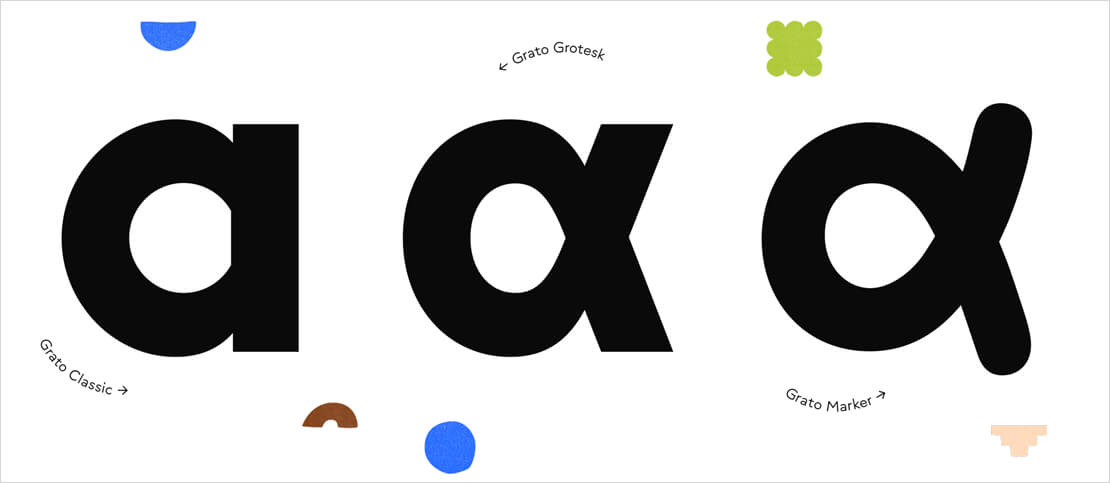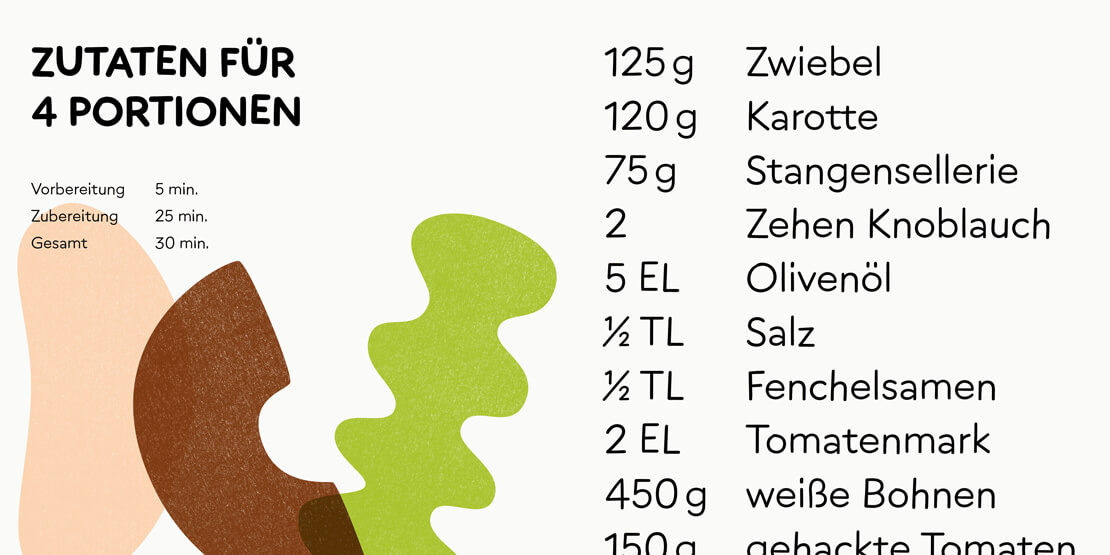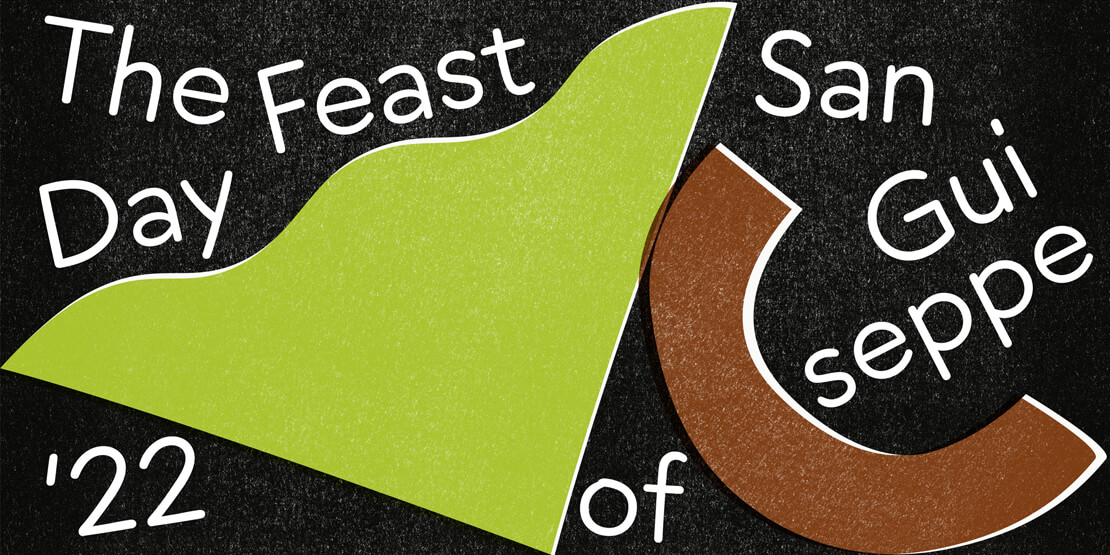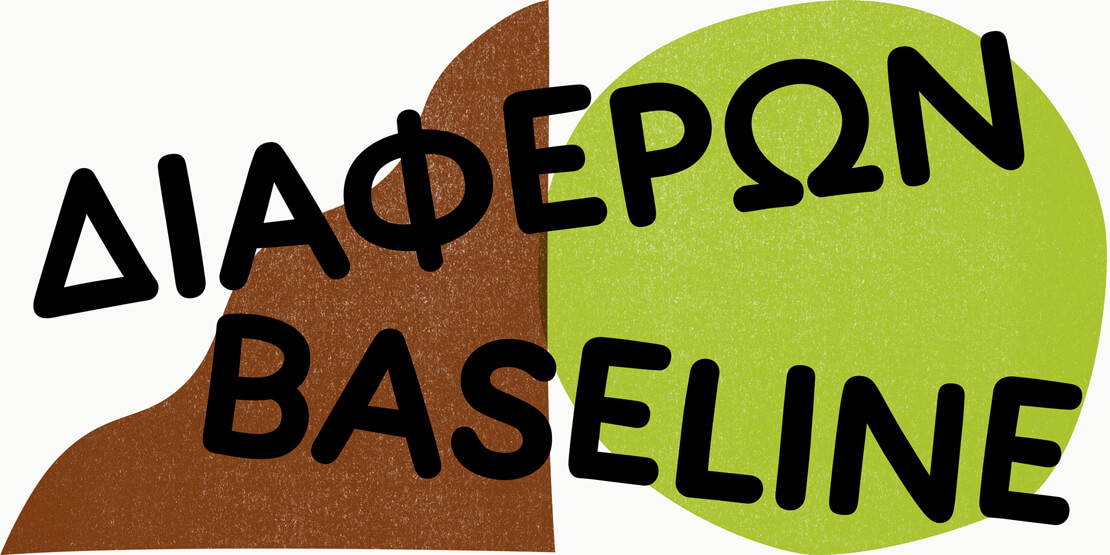
Grato Marker: Handgeschrieben und geometrisch
»Grato Marker« ist ein Hybrid aus geometrischer Form und handschriftlicher Methode. Die abgerundete und leicht verspielte Schriftfamilie von Teja Smrekar und Jakob Runge ist neu bei TypeMates erschienen.
»Grato Marker« lässt Stämme leicht kippeln, die Grundlinien hüpfen und variiert die Buchstabengröße auf spielerische Art und Weise. Die handschriftlich interpretierten Buchstaben sollen bewusst etwas wackelig wirken und für ein organisches Gefühl sorgen.
Basierend auf handschriftlichen Werkzeugen ist sie stilistisch als Begleiter zu eher nüchtern wirkenden Sans-Serif-Schriften gedacht, da sie unabhängig bleibt und ihrem eigenen Stil folgt. Daraus ergeben sich typische Einsatzgebiete wie Kinderbücher, informelle Angebote, offenherziges Packaging oder natürliche Marken.
Anpassbares Textbild
»Grato Marker« deckt ähnlich realen Strichen von Filzstiften ein kompaktes Gewichtsspektrum ab, mit insgesamt vier Stärken von leicht bis fett. Das Textbild lässt sich durch drei Formatsätze anpassen: Ein Set für ein serifenbetontes „l“ zur Unterscheidung vom großen „I“, ein weiteres für den Wechsel in einen eher kindlichen Stil mit einstöckigem „a“ sowie ein drittes Set für den Wechsel zu einem markanten doppelstöckigen „g“.
Durch muttersprachliche Expertise geprüft, unterstützt die Marker mehr als 270 Sprachen, einschließlich Vietnamesisch.